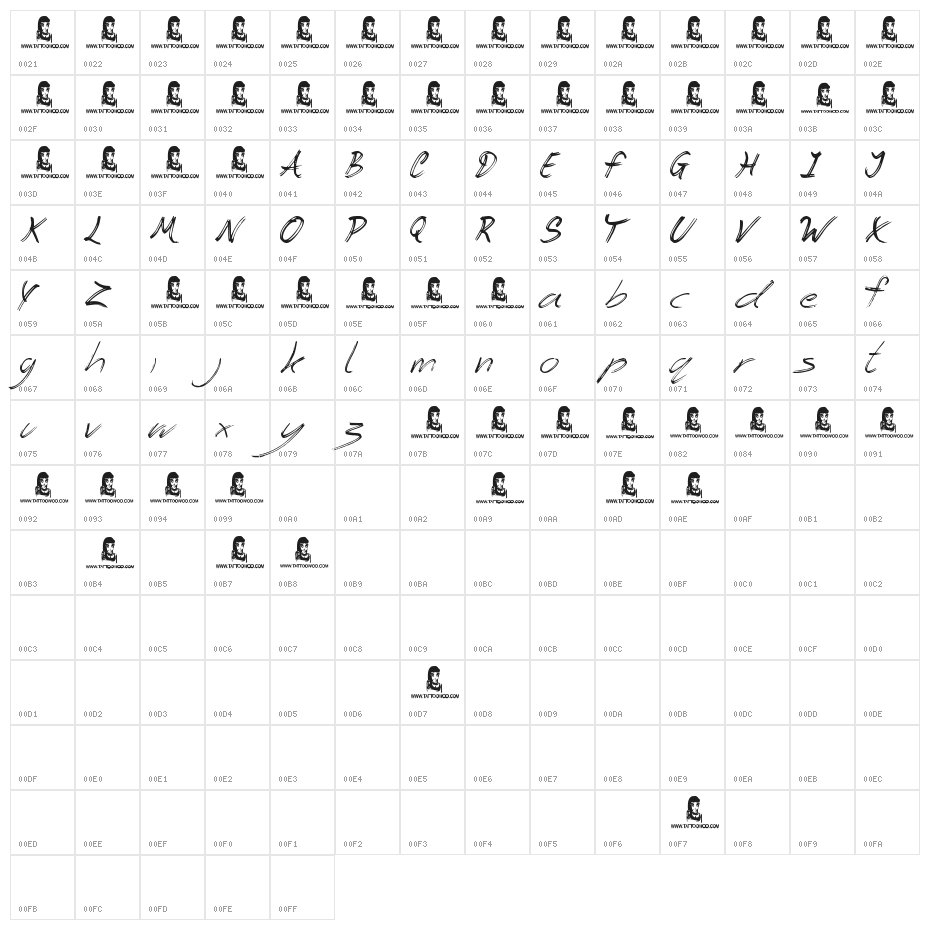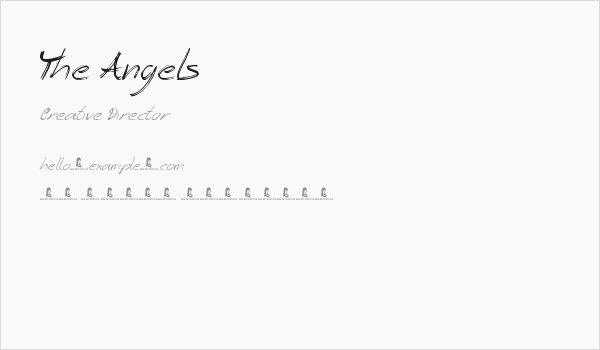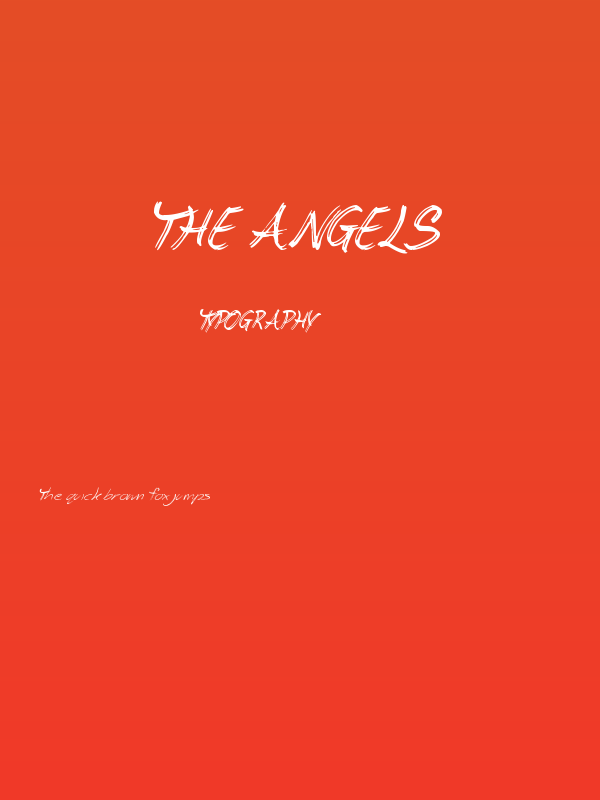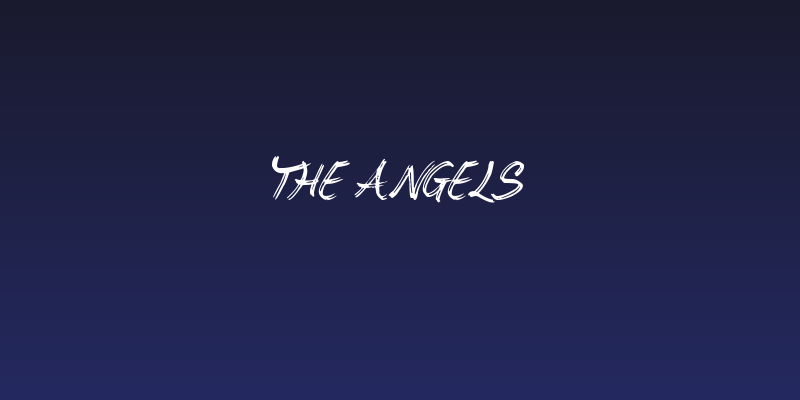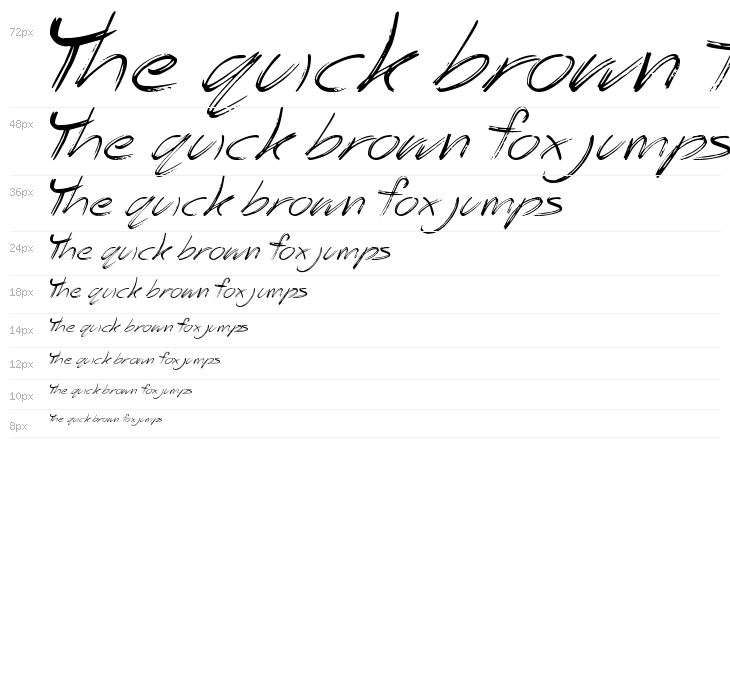
The Angels Font
| Caso de uso | Logos, Headlines, Artistic designs |
| Projetos propostos | Ideal for tattoo designs, album covers, posters, and other creative projects requiring a bold and artistic touch. |